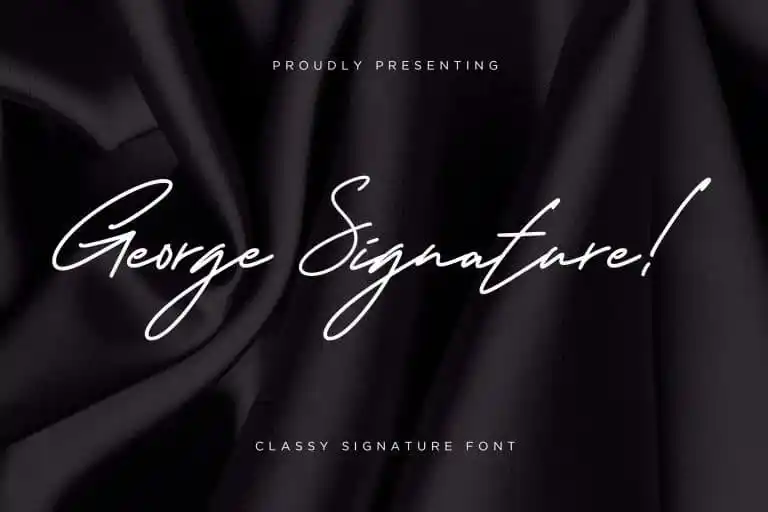
George Handwritten Font – Download Grátis
A George Handwritten Font é a escolha perfeita para quem busca uma fonte elegante e sofisticada para seus projetos. Esta letra cursiva possui curvas únicas que oferecem um toque refinado, destacando-se com sua própria grife personalizada e estilo de escrita elegante. A George Signature é ideal para qualquer projeto que necessite de um toque autêntico e original do tipo de escrever — desde identidades corporativas e logotipos até embalagens de produtos e convites de casamento. Suas linhas fluidas e curvas suaves garantem uma aparência sofisticada, perfeita para criar designs atraentes que combinam elegância com modernidade. A fonte é uma opção perfeita para designers e criativos em busca de um tom que destaque seus projetos, seja por meio da criação de logotipos ou embalagens de produtos personalizadas. Na era digital, este estilo autêntico de escrita adquire ainda mais valor. George Signature se adapta perfeitamente para a necessidade atual de incluir um toque humano em suas campanhas digitais e redes sociais, garantindo que sua marca permaneça vívida e memorável. Seja o próximo projeto, seja ele grande ou pequeno, você certamente encontrará uma maneira criativa de usar esta fonte inovadora para se destacar no mercado.